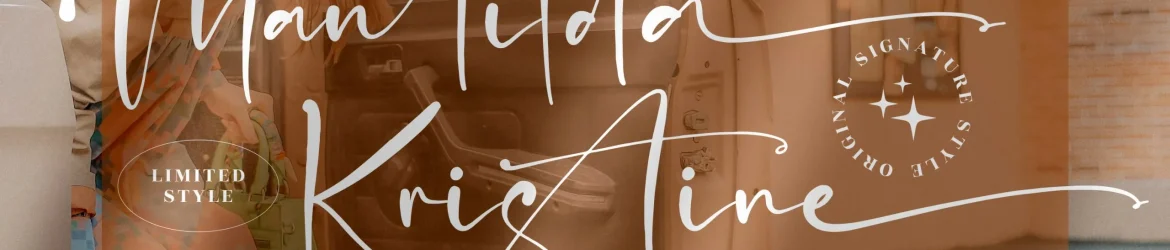
Mantilda Kristine Font – Download Grátis
A Mantilda Kristine Font é uma elegante tipografia para assinaturas do estúdio Perspectype Studio, perfeita para qualquer projeto, desde logotipos e projetos de marca até embalagens de produtos, sacolas de shopping, cartões de lembrança, capas de livros, cartões de nome, postais, etiquetas, fotografia e até mesmo eventos especiais. Seja você criando um produto de luxo ou uma campanha publicitária sofisticada, a Mantilda Kristine Font é sua escolha ideal para garantir que seu trabalho se destaque com uma assinatura de alta qualidade. Com seus traços finos e suaves, essa fonte manuscrita é o toque final perfeito para qualquer projeto. Seja você um designer gráfico, um empreendedor ou até mesmo alguém com uma paixão pela fotografia, a Mantilda Kristine Font pode ser usada para criar um design único e de alta qualidade que tornará seu trabalho incomparável.